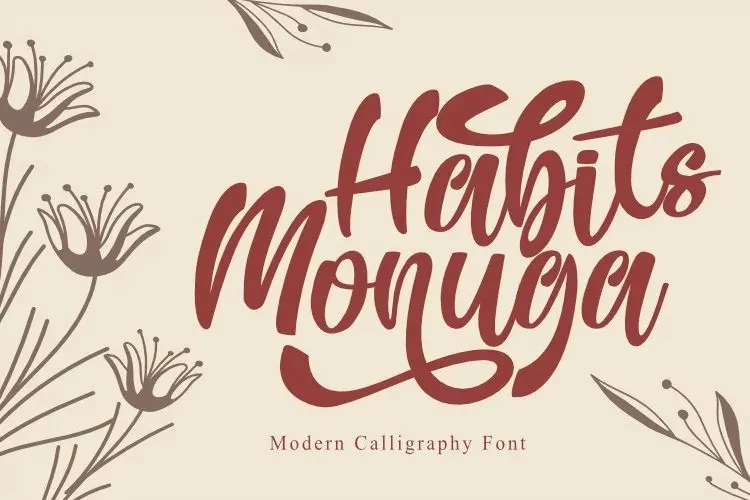
Habits Monuga Font – Fonte Grátis
Habits Monuga Font
A fonte Monuga Script é uma escolha perfeita para aqueles que buscam um estilo elegante e versátil para textos de texto ou até mesmo design gráfico. Este fonte está projetado para ser fácil de ler, tornando-o especialmente conveniente para aplicativos exigentes como sites corporativos, anúncios publicitários ou qualquer conteúdo digital que necessite de uma leitura confortável ao longo do dia. A Monuga Script não apenas oferece um aspecto atraente e sofisticado, mas também permite o uso de caracteres alternativos com composição de letras perfeita, tornando-a uma ferramenta versátil para estilos diversos, desde editoriais até elementos digitais criativos. Com sua facilidade de leitura e beleza intrínseca, a Monuga Script será um verdadeiro ativo em seu catálogo de fontes. Ela possui o potencial incrível de tornar qualquer projeto mais atrativo e impecável, seja ele uma publicação, site ou design gráfico. Como designer criativo usando 99designs, você vai adorar a ideia de ter um ativo que pode melhorar tanto sua versatilidade quanto o seu impacto visual em projetos finais, garantindo que cada detalhe da sua criação se destine ao máximo possível à experiência do usuário.